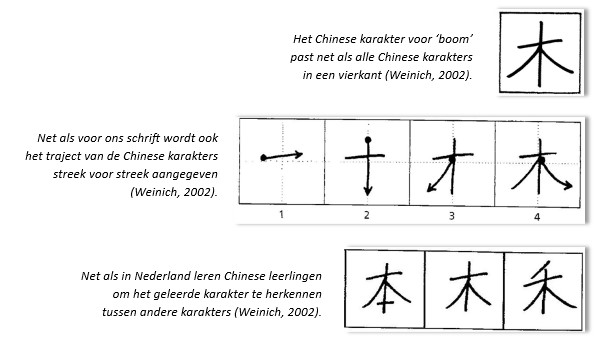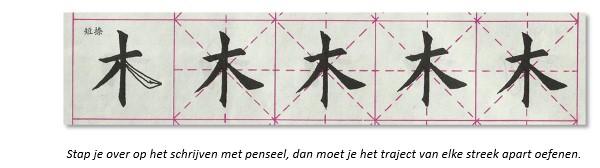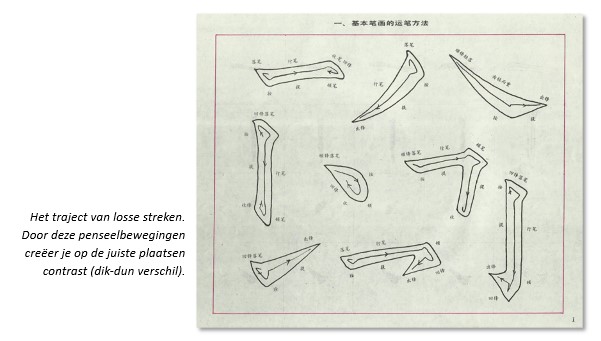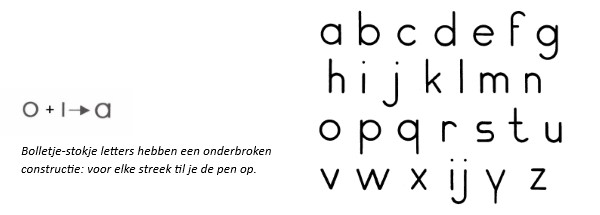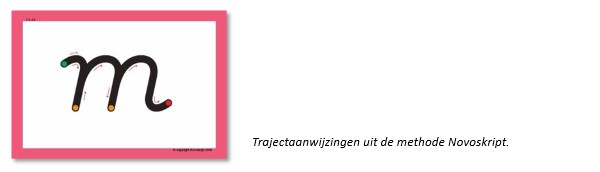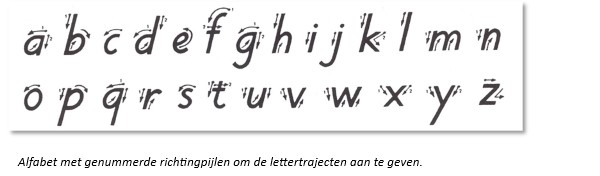
Wat komt in dit hoofdstuk aan bod?
Dit hoofdstuk behandelt de achtergrondinformatie bij 3.1.6: ‘Traject’. De student heeft deze informatie nodig om de opdrachten uit het werkschrift te kunnen maken.
Constructie
Binnen de elementaire schrifthandeling heeft elk teken (het statische aspect ‘vorm’) een eigen traject (het dynamische aspect ‘proces’) – een kenmerkende route om een letter of cijfer te schrijven. Een hoofdletter ‘A’ construeer je bijvoorbeeld uit losse streken en met een heel ander traject dan de kleine letter ‘a’. Ieder schriftteken, of het nu gaat om de letters van ons Latijnse alfabet of bijvoorbeeld om Chinees schrift, maak je volgens een voorgeschreven traject.
Ten aanzien van de constructie van het traject onderscheid je twee aspecten:
- Cursief schrift en onderbroken schrift.
- Onverbonden schrift en verbonden schrift.
Cursief of onderbroken schrift
Cursief
De term ‘cursief’ betekent letterlijk ‘lopend’ (Latijn: currere = lopen).
We noemen letters cursief of lopend als je ze volgens een bepaald traject, in een ononderbroken doorgaande beweging schrijft zonder je pen op te tillen. In cursief schrift komen streken voor waarin het front van de pen zich omkeert (Noordzij, 1991). Bij letters als ‘a’ en ‘n’ beweeg je dan deels over een vorige streek terug.
De term ‘cursief’ zegt dus iets over de constructie van het schrift, de wijze waarop je het schrift schrijft en niet over de vraag of het rechtop of schuin staat.
In de 15e eeuw ontstond in Italië een vlot koopmansschrift, dat met een vloeiende doorgaande beweging werd geschreven. Omdat het zo’n goed schrijfbare heldere letter was, werd dit schrift door veel wetenschappers overgenomen. Naar de plaats van ontstaan werd het ook wel ‘Italic’ genoemd. In typografie is de term ‘cursief’ een synoniem geworden voor ‘schuin schrift’ en wordt dat ‘Italic’ genoemd. Je ziet dat nu nog aan de letter ‘I’ in je menubalk ‘start’.
De letter die in Italië ontstond vormt dus de basis van ons handschrift.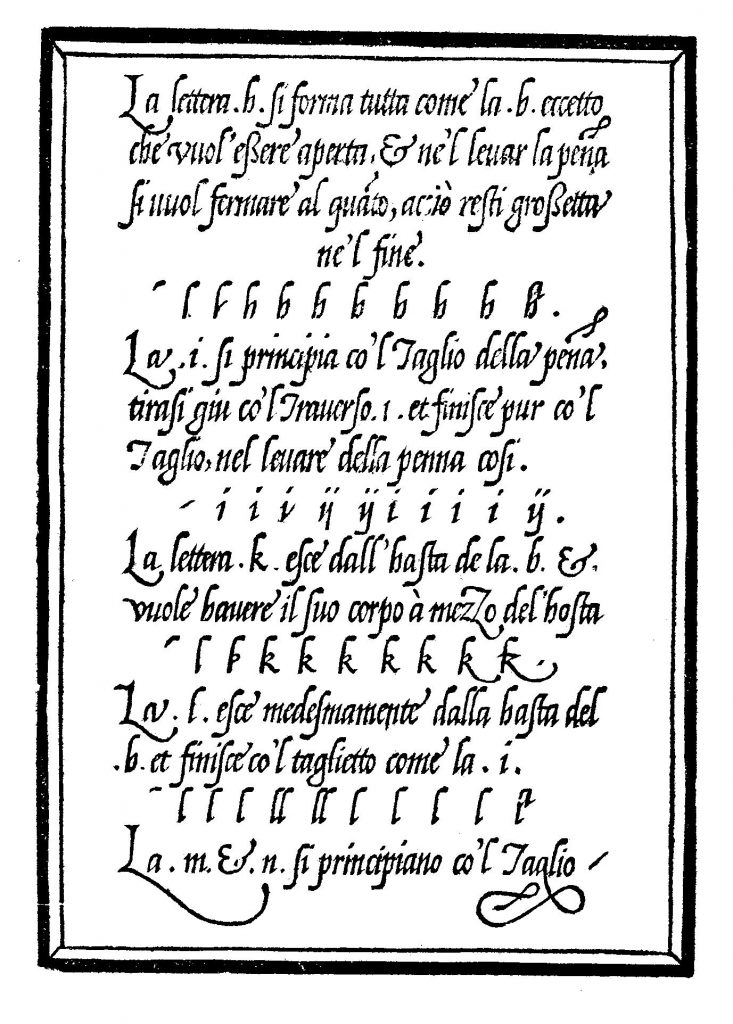
Hoe ontstond dit schrift? Briem (1985) lichtte dit met illustraties toe aan de hand van de letter ‘F’.
Het maken van een letter kun je vergelijken met het afleggen van een route. In je alledaagse leven loop je bepaalde routes en snij je bochten af als dat sneller gaat. Er ontstaat op zo’n plek een nieuwe vorm: een ‘olifantenpaadje’. Op die manier is ook altijd gezocht naar de meest efficiënte manier om letters te schrijven. De Romeinen namen het schriftteken ‘F’ over van de Grieken.
Het traject van de ‘F’ verliep als volgt: eerst de verticale neerhaal, vervolgens de bovenste arm van links naar rechts en tenslotte de onderste arm in het midden van de stam.
Op papyrus werd een cursieve langere ‘f’ geschreven volgens ditzelfde traject. Doordat de pen niet werd opgetild, zag deze ‘f’ er anders uit.
Midden 15e eeuw liet men de lange neerhaal eindigen in een lus naar links. Dat maakte de ‘f’ lastig te onderscheiden van de lange ‘s’ die toen nog in gebruik was. Des te belangrijker werd de dwarsstreep van de ‘f’. In de 18e eeuw liet men de onderste lus van de ‘f’ naar rechts buigen, om hem duidelijker te onderscheiden van de lange ‘s’ waarvan de lus naar links boog. En zo schrijven wij de verbonden ‘f’ nog steeds in ons handschrift.
Bekijk je het lettertraject goed en vergelijk je het met het oorspronkelijke lettertraject van de Romeinen, dan zie je dat er eigenlijk niet veel veranderd is; het traject van onze ‘f’ heeft hetzelfde bewegingspatroon, alleen omgekeerd en achterstevoren.
Onderbroken
Letters die je streek voor streek schrijft en die je dus uit losse halen opbouwt, noem je ‘ onderbroken’ schrift. Zulke letters maak je streek voor streek (haal voor haal) en het front beweegt zich altijd in een richting (Noordzij, 1991). De letterdelen worden tegen elkaar aan geplakt en er zijn geen stop-en-keerpunten. Deze letters hebben een ‘onderbroken’ constructie in tegenstelling tot de ‘cursieve’ (lopende, ononderbroken en kerende) constructie zoals hierboven beschreven. De bolletje-stokje letters zijn een voorbeeld van een onderbroken constructie. Voor elke streek til je de pen op.
Er zijn aanwijzingen dat er bij de start van handschriftonderwijs nauwelijks verschil in aanleertempo is tussen blokschrift en onverbonden cursief schrift, noch wat betreft de kwaliteit van het schrijven noch wat betreft de schrijfsnelheid (Karlsdottir, 1996). Ook ten aanzien van het leren lezen en spellen is geen verschil in effect gemeten (Karlsdottir, 1996b). In deze onderzoeken werden twee groepen leerlingen vergeleken. De ene groep leerde schrijven met onverbonden schrift en de andere groep leerde schrijven met verbonden schrift. Beide groepen leerden het volgend jaar verbonden schrijven. Maar of het in deze onderzoeken om onverbonden onderbroken schrift of om onverbonden cursief schrift ging, is echter niet vermeld.
Onverbonden of verbonden schrift
De termen onverbonden (los) schrift of verbonden (vast) schrift, verwijzen naar de woordverbinding. Ze zeggen iets over de vraag of je de letters los schrijft of dat je de letters binnen een woord verbindt en dus ‘woordcursief’, aan elkaar schrijft.
Voor het lettertraject maakt het niet uit of je onverbonden of verbonden schrijft, want je beweegt altijd naar de volgende letter toe. In feite schrijf je onverbonden schrift met luchtverbindingen.
Daarmee voer je het traject niet met twee dimensies (op-neerhalen en links-rechtsrichting) maar met drie dimensies uit.
In de aanvankelijke fase lijkt het eenvoudiger om los te schrijven. De lijnvoering is dan nog niet zo strak en omdat bij los schrift verhoudingsgewijs meer neerhalen op papier staan, oogt het netter. Maar het schrijven wordt telkens onderbroken. Na iedere letter stop je, til je de pen op en moet je het startpunt voor de nieuwe letter bepalen en je motoriek daarop aansturen. Motorisch is los schrijven dus complexer.
Bovendien zijn er aanwijzingen dat bij 6-jarige leerlingen, dus vanaf de start van groep 3, de visuele mogelijkheden voor het aanleren van lopend verbonden schrift voldoende aanwezig zijn (Vinter & Chartrel, 2008).
Bovendien leer je met verbonden schrift het lettertraject plus het woordtraject actief aan. De doorgaande beweging is een doel op zich. Aan het product op papier kun je achteraf ook zien of je leerling met een goed traject heeft geschreven.
Daarbij bevestigt onderzoek van Palmis et al. (2017) dat naast letters ook hele woorden opgeslagen worden in het lange termijn geheugen wat het leren lezen ondersteunt.
In de fase van handschriftontwikkeling (groep 7-8) kunnen leerlingen onderzoeken of een verbonden, een matig verbonden of onverbonden schrift (met luchtverbindingen) beter bij hen past. Het schrift van volwassen, ervaren schrijvers is vaak een combinatie van verbonden en onverbonden schrift.
← Werkschrift: 3.1 Proces – Opdracht 26: Begrippen
Uitvoering
Om het traject correct te kunnen uitvoeren zijn volgens Teulings en Thomassen (1985) drie deelvaardigheden nodig:
- Het opslaan van relevante bewegingsinformatie in het motorisch geheugen.
- Het daaruit ophalen van de gewenste informatie.
- Het vertalen van de opgehaalde informatie in de bewegingsuitvoering.
Opslaan van relevante bewegingsinformatie
Het traject is een constante structuur met een vaste volgorde, een vaste draairichting en een vaste verhouding tussen de op- en neerhalen van de letter. Om het traject goed in te slijpen en op te slaan in het motorisch geheugen, dien je het altijd in dezelfde volgorde te oefenen.
Bijvoorbeeld de ‘e’ altijd: schuin omhoog, naar links, de draai tot onderaan en schuin omhoog weer verder gaan. Een lettertraject laat zich in enkele uren oefenen al automatiseren. Dat het lettertraject zich in je geheugen nestelt, merk je aan hoe lastig het is om een bepaalde lettervorm in je handschrift aan te passen, bijvoorbeeld als je van de doorverbonden lusjes-t wilt overstappen op een t-met-streepje.
Ophalen van de gewenste informatie
Het in de juiste volgorde ophalen van het lettertraject uit het geheugen vindt plaats tijdens het schrijven. Daardoor kun je een letterreeks die bestaat uit verschillende losse eenheden van opgeslagen bewegingsinformatie vloeiend schrijven. Dit kun je het beste oefenen door een bepaalde letter (traject) in combinatie met andere letters te oefenen. Het louter herhalen van een bepaalde letter is minder zinvol omdat bij een letterpaar, bijvoorbeeld ‘ee’ de bewegingsinformatie voor de tweede letter aanmerkelijk sneller wordt opgehaald. Dat lijkt erop te wijzen dat het ophalen van de tweede letter niet meer in extenso hoeft te worden uitgevoerd en voor een training is dat juist wel van belang. Daarom is het zinvoller om naast het oefenen van de losse letter ‘e’ en het letterpaar ‘ee’, wisselende lettercombinaties te oefenen, zoals ‘en’, ‘er’, ‘ge’, ‘be’, …
Vertalen van de informatie in de bewegingsuitvoering
Om het traject correct te leren uitvoeren vertaal je de opgehaalde geheugeninformatie in spiercommando’s, dat wil zeggen in concrete krachtstootjes van een bepaalde duur. Je oefent dit door te variëren in snelheid, proprioceptieve terugkoppeling (terugkoppeling uit spiergevoel en tast), schriftgrootte, schrifthelling en ligging van het schrijfvlak. Aan het begin doe je dat bewust. Naarmate het inslijpen vordert, steeds minder bewust.
Op grond van kennis van de vorm bepaal je of en hoe je het traject van een volgende letter bijstuurt. Deze uitvoeringswijzen worden niet opgeslagen in het motorisch geheugen, maar tijdens de bewegingsuitvoering ingevuld.
Snelheid
Aanvankelijk voeren leerlingen het traject van een letter van steunpunt naar steunpunt uit. Door het traject van letters via een opbouw in moeilijkheidsgraad met wisselende snelheid te automatiseren, blijkt de schrijfsnelheid te verbeteren. Te denken valt aan ‘c’- ‘a’- ‘d’- ‘g’- …
Proprioceptieve terugkoppeling
Proprioceptieve terugkoppeling wil zeggen, de informatie die je haalt uit je spiergevoel en je tast. Concreet het gevoel dat je krijgt uit de wrijving tussen penpunt en drager. Tijdens de aanleerfase kun je deze proprioceptieve terugkoppeling versterken door een ruwe combinatie te kiezen zoals een potlood op stroef papier (bijvoorbeeld koffiefilters), een krijtje op het bord. Het gaat hierbij om tegenkrachten (wrijving) die in relatie staan tot de krachten die nodig zijn voor de beweging zelf (het schrijven). Omdat luchtschrijven in het geheel geen weerstand biedt is dat in dit kader minder zinvol. Ook de combinatie balpen-papier geeft weinig informatie. Wel veel informatie geven de combinaties potlood op koffiefilter, grip-tec op papier en vulpen op papier.
Schriftgrootte
Ook schriftgrootte is niet in het motorisch geheugen opgeslagen. Dat wil zeggen dat je een aangeleerde letter direct zowel groot als klein kunt schrijven. Nu blijkt variatie in schriftgrootte het leren schrijven van een bepaalde vormverhouding te bevorderen. Het gaat daarbij om letters met een romphoogte van 5mm tot ‘groot’. De grootte van 5mm blijkt de kleinste schrijfbeweging te zijn die leerlingen naar verhouding even snel kunnen uitvoeren als volwassenen. Door groot te oefenen, train je tegelijkertijd de grote progressie, dat wil zeggen het bewegen van de schrijfarm van links naar rechts over het papier.
Schrifthelling en ligging van het schrijfvlak
Volwassenen blijken hun schrifthelling en de ligging van hun schrijfvlak vrij te kunnen manipuleren. Deze liggen dus niet in het motorisch geheugen opgeslagen. Ze moeten ook voortdurend tijdens het opschuiven over de regel worden aangepast, want aan het eind van de regel schrijf je op een andere plaats dan aan het begin van de regel. En ook door het opschuiven binnen een woord maakt je hand steeds een andere hoek met de regel. Schrifthelling en de ligging van het schrijfvlak dienen daarom onderzocht te worden met experimenten na het aanvankelijk schrijven.
Didactische aanwijzingen
- Houd het traject constant: oefen een letter altijd met één en hetzelfde traject.
- Voorzie letters op verschillende manieren van trajectinstructie:
- start-, keer- en eindpunt. Je laat deze markeren met groen voor het startpunt, oranje voor het stop-en-keerpunt en rood voor het eindpunt van de letter.
- genummerde richtingpijlen. Je laat met richtingpijlen het traject van de letter aanwijzen.
- verbale begeleiding. Je benoemt het traject, al dan niet in versvorm. Bijvoorbeeld ‘links de draai tot onderaan, omhoog, omlaag en verder gaan…’ voor de letter ‘a’.
- Varieer tijdens de aanleerfase:
- de lettercombinaties: de losse letter, het letterpaar, in combinatie met andere letters;
- de snelheid;
- de materiaalcombinaties: kies materiaal dat de wrijving vergroot om de proprioceptieve terugkoppeling te versterken;
- de schriftgrootte.